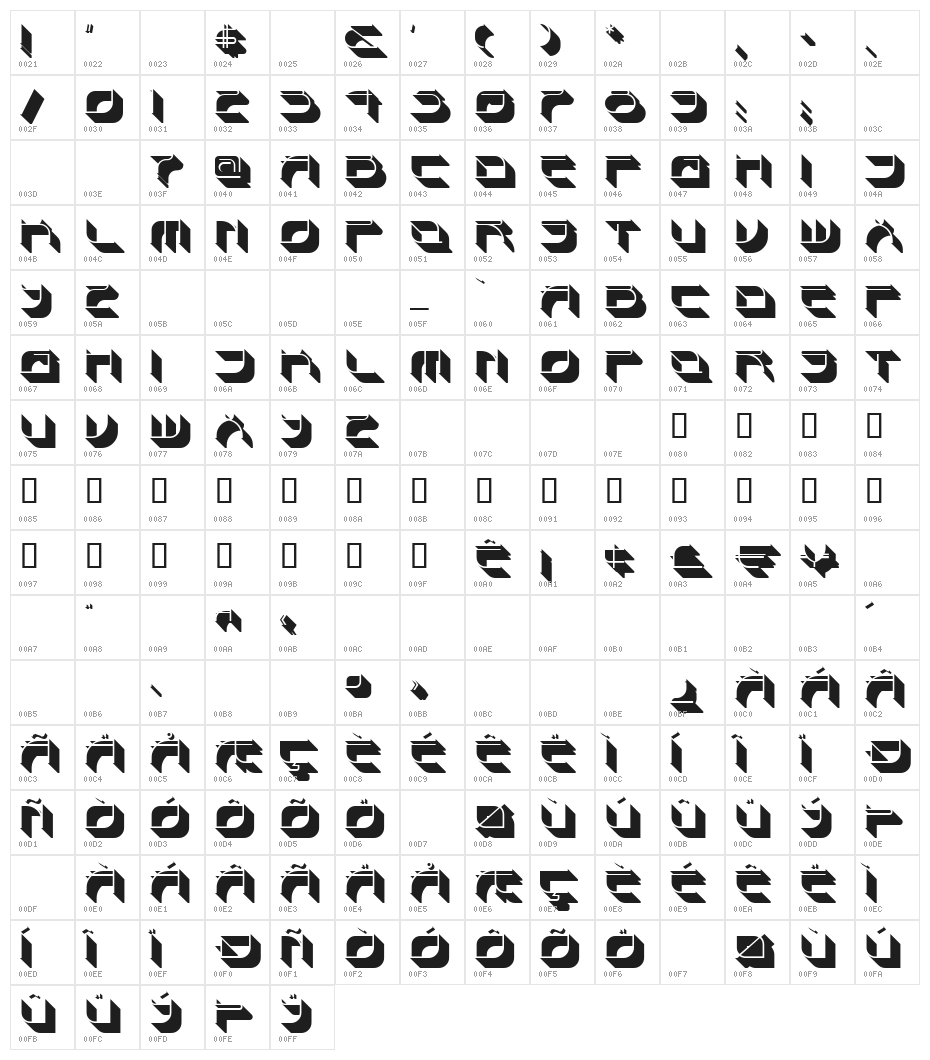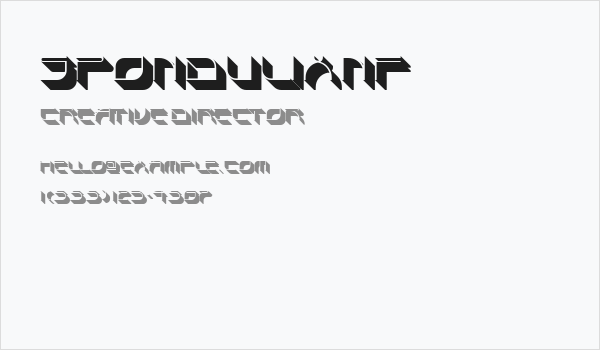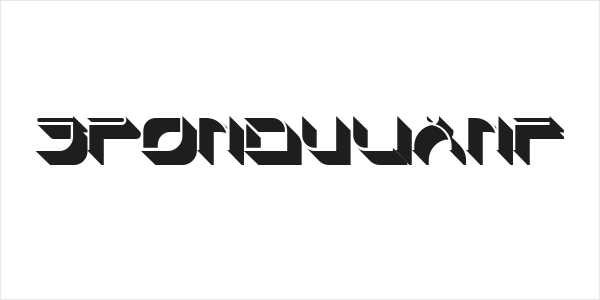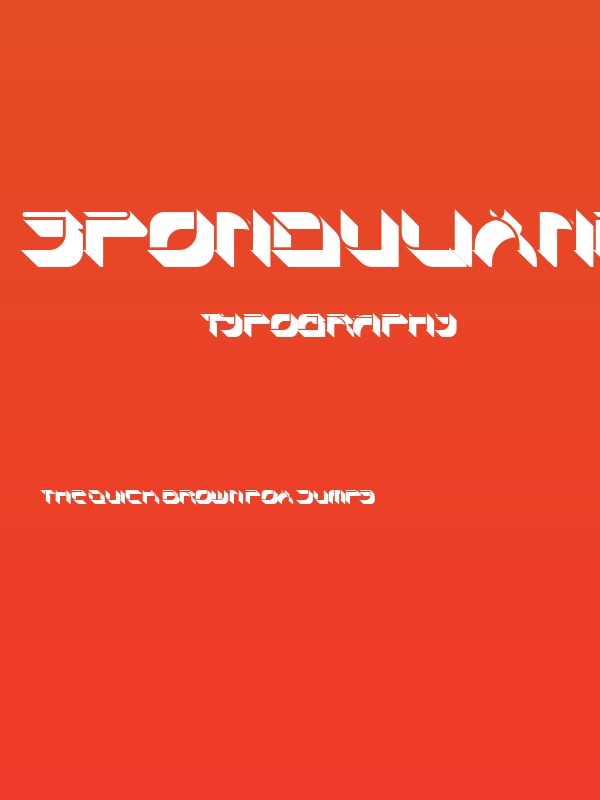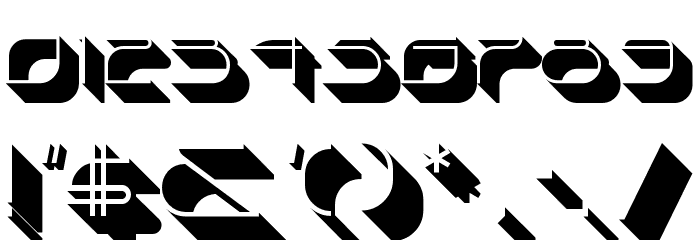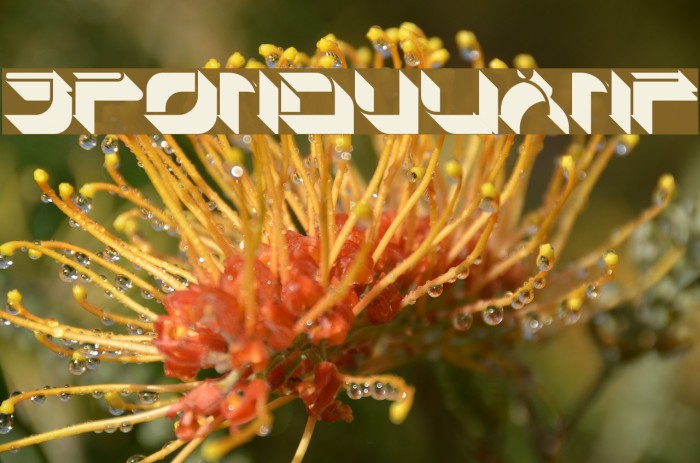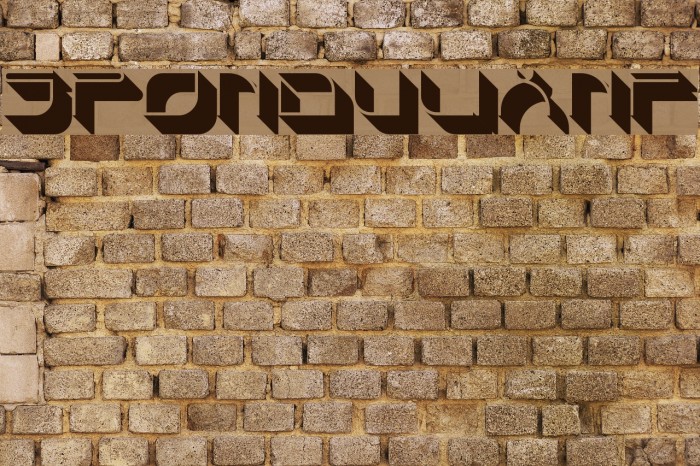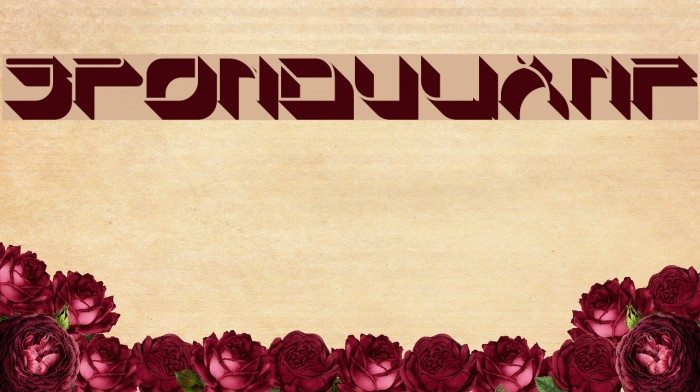
SpondulixNF Font
✎ 3D
| Gesamtstil | Futuristic |
| Vorgeschlagene Projekte | Ideal for sci-fi themed posters, video game graphics, tech branding, and modern art installations. |